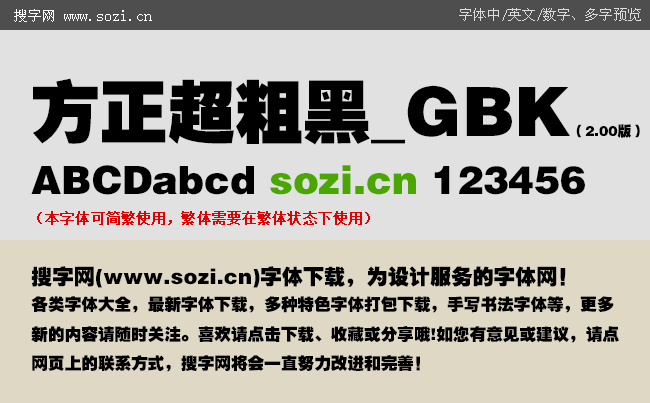
方正超粗黑_GBK
搜字網(wǎng)提供一款方正超粗黑_GBK中文字體下載,方正超粗黑是一款字形端莊的中文字體,該字體字體結(jié)構(gòu)端正、重心平穩(wěn)、美觀實(shí)用、清晰醒目。GBK編碼收錄漢字更全,適合應(yīng)用于廣告設(shè)計(jì)、名片設(shè)計(jì)、包裝印刷、產(chǎn)品設(shè)計(jì)等應(yīng)用。